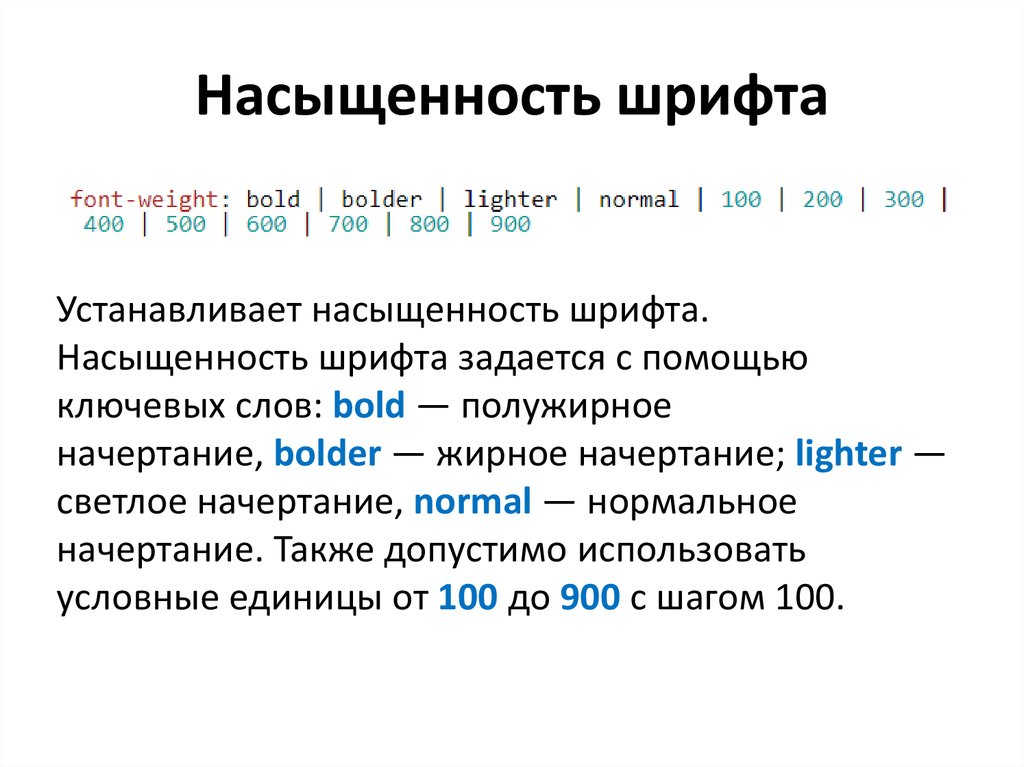
Начертание полужирное в css
Курсив и жирный шрифт CSS — учебник CSS
Чтобы сделать шрифт жирным в CSS либо задать ему курсивное начертание, вам пригодятся такие свойства, как font-weight и font-style. Ниже мы разберемся, какие значения могут быть использованы для этих свойств.
Жирный шрифт в CSS: свойство font-weight
Управлять жирностью шрифта в CSS можно с помощью значений свойства font-weight:
| bold | Полужирный шрифт |
| normal | Обычный шрифт |
| bolder | Более жирный шрифт, чем у родителя |
| lighter | Менее жирный шрифт, чем у родителя |
| inherit | Наследует значение родителя |
| Числовое значение от 100 до 900 | От очень тонкого до очень жирного шрифта |
Пример записи:
p { font-weight: bold; }Насыщенность шрифта вы можете регулировать с помощью ключевых слов bold (полужирное), normal (обычное начертание), bolder (более жирное, чем у родителя), lighter (менее жирное, чем у родителя), inherit (такое же, как у родителя), а также используя числовые значения 100, 200, 300, 400, 500, 600, 700, 800 и 900, настраивая жирность шрифта от самого тонкого до самого плотного.
Примечание: числовые значения от 100 до 900, означающие толщину шрифта, сработают только в том случае, если у шрифта, с которым вы работаете, предусмотрены эти варианты начертания. Данные значения используются в основном с веб-шрифтами, о которых мы говорили в первой подглаве.
Курсив в CSS: свойство font-style
Задать курсивное начертание шрифта можно при помощи значений свойства font-style:
| italic | Курсивный шрифт |
| oblique | Наклонный шрифт |
| normal | Обычный шрифт |
| inherit | Наследует значение родителя |
Пример записи:
p { font-style: italic; }Чтобы сделать курсив в CSS, используйте значение italic. Второе значение в таблице – oblique – означает наклонное начертание и отличается от курсива тем, что все символы с обычным начертанием просто наклоняются вправо, в то время как курсив – это отдельно созданный вариант начертания шрифта, похожий на рукописный.
Значение normal устанавливает обычный стиль шрифта, а inherit позволяет наследовать стиль родителя.
Курсив и жирный шрифт CSS — учебник CSS
Чтобы сделать шрифт жирным в CSS либо задать ему курсивное начертание, вам пригодятся такие свойства, как font-weight и font-style. Ниже мы разберемся, какие значения могут быть использованы для этих свойств.
Жирный шрифт в CSS: свойство font-weight
Управлять жирностью шрифта в CSS можно с помощью значений свойства font-weight:
| bold | Полужирный шрифт |
| normal | Обычный шрифт |
| bolder | Более жирный шрифт, чем у родителя |
| lighter | Менее жирный шрифт, чем у родителя |
| inherit | Наследует значение родителя |
| Числовое значение от 100 до 900 | От очень тонкого до очень жирного шрифта |
Пример записи:
p { font-weight: bold; }Насыщенность шрифта вы можете регулировать с помощью ключевых слов bold (полужирное), normal (обычное начертание), bolder (более жирное, чем у родителя), lighter (менее жирное, чем у родителя), inherit (такое же, как у родителя), а также используя числовые значения 100, 200, 300, 400, 500, 600, 700, 800 и 900, настраивая жирность шрифта от самого тонкого до самого плотного.
Примечание: числовые значения от 100 до 900, означающие толщину шрифта, сработают только в том случае, если у шрифта, с которым вы работаете, предусмотрены эти варианты начертания. Данные значения используются в основном с веб-шрифтами, о которых мы говорили в первой подглаве.
Курсив в CSS: свойство font-style
Задать курсивное начертание шрифта можно при помощи значений свойства font-style:
| italic | Курсивный шрифт |
| oblique | Наклонный шрифт |
| normal | Обычный шрифт |
| inherit | Наследует значение родителя |
Пример записи:
p { font-style: italic; }Чтобы сделать курсив в CSS, используйте значение italic. Второе значение в таблице – oblique – означает наклонное начертание и отличается от курсива тем, что все символы с обычным начертанием просто наклоняются вправо, в то время как курсив – это отдельно созданный вариант начертания шрифта, похожий на рукописный.
Значение normal устанавливает обычный стиль шрифта, а inherit позволяет наследовать стиль родителя.
Далее в книге: строчные и заглавные буквы с помощью свойства CSS text-transform.
Как сделать в CSS жирный шрифт?
Чтобы сделать в CSS жирный шрифт, следует использовать ряд стандартных команд. Но можно воспользоваться и нестандартными вариантами, которые дают интересный эффект. Жирное начертание применяется для выделения строго определенного фрагмента текста. CSS нам помогает присвоить такой шрифт любому словосочетанию или даже отдельной букве. Если вы до сих пор используете HTML-теги для достижения этого эффекта, вам нужно пересмотреть свои взгляды на программирование, так как каскадные таблицы стилей дают вам как разработчику больше возможностей. О некоторых из них мы поговорим в этой статье.
Кстати, в одной из последних статей мы рассматривали такое понятие, как Css стили принятые по умолчанию, для оформления элементов в Html коде, если в файле таблиц каскадных стилей для этих элементов ничего не задано. Так вот там, например, для заголовков h2-H6 и тегов логического и физического выделения жирным (strong и B) определен стиль font weight со значением bolder: